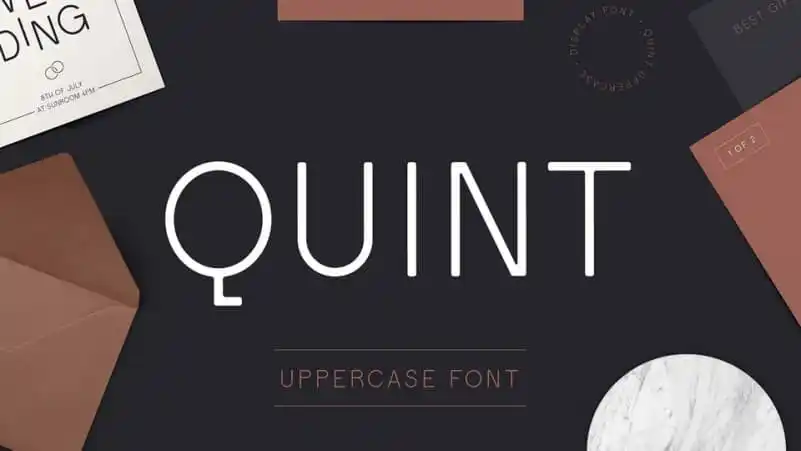
A Quint Sans Serif Font é uma escolha perfeita para aqueles que buscam uma fonte moderna e versátil. Esta nova all-caps sans serif adquirem sua elegância através da combinação única de Sharpness, um elemento atrativo que equilibra a geometria com detalhes arredondados criando formas escritográficas suaves e sofisticadas. Com sua estética contemporânea que incorpora elementos retro, a Quint Sans Serif Font se destaca como uma escolha ideal para o design de headlines, logotipos, marca, cartazes e revistas. Com seu estilo limpo e moderno, combinado com sutis detalhes vintage, essa fonte oferece um contraponto interessante que pode fazer com que seu conteúdo seja ainda mais atraente e memorável. Seja para projetos de design gráfico ou publicitários, a Quint Sans Serif Font é uma escolha confiável e versátil, prometendo agregar valor ao seu trabalho.